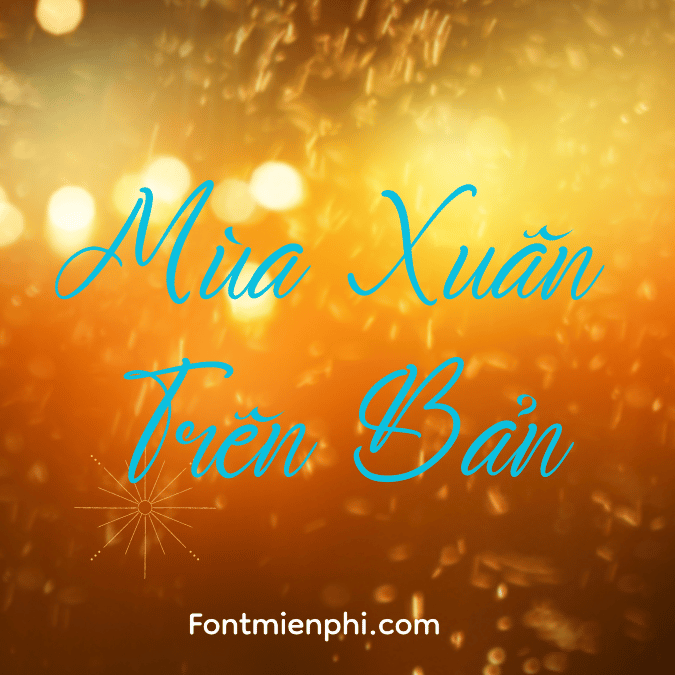
Font Việt hóa 1FTV VIP Martinez Gauttaro , Font Việt hóa tết
Font Việt Hóa 1FTV VIP Martinez Gauttar – “Đẳng Cấp Từng Nét Chữ”
Đặc điểm nổi bật:
• Phong cách sang trọng, hiện đại: Lấy cảm hứng từ những dòng chữ cao cấp trong thiết kế châu Âu, kết hợp nét thanh mảnh và độ dày cân đối, tạo sự hài hòa tuyệt đối.
• Tối ưu hóa tiếng Việt: Hỗ trợ đầy đủ bộ dấu, Unicode, đẹp mắt ở mọi kích thước từ headline đến body text.
• Chi tiết tinh xảo: Nét chữ có độ bo tròn mềm mại, điểm nhấn là các đường cong uyển chuyển, phù hợp với thiết kế cao cấp.
Ứng dụng đa dạng:
• Nhận diện thương hiệu (logo, slogan công ty, tài liệu doanh nghiệp).
• Thiết kế bao bì sản phẩm cao cấp (mỹ phẩm, rượu vang, thời trang).
• Tạp chí, poster quảng cáo, website phong cách tối giản nhưng đẳng cấp.
Gợi ý phối màu:
• Tông trung tính: Đen (#000000), trắng ngà (#F8F4E3), xám khói (#6C757D).
• Tông nổi bật: Xanh navy (#0A2463), vàng ánh kim (#D4AF37).
“Martinez Gauttar – Sự kết hợp hoàn hảo giữa tinh tế và đẳng cấp, nâng tầm thương hiệu của bạn!”